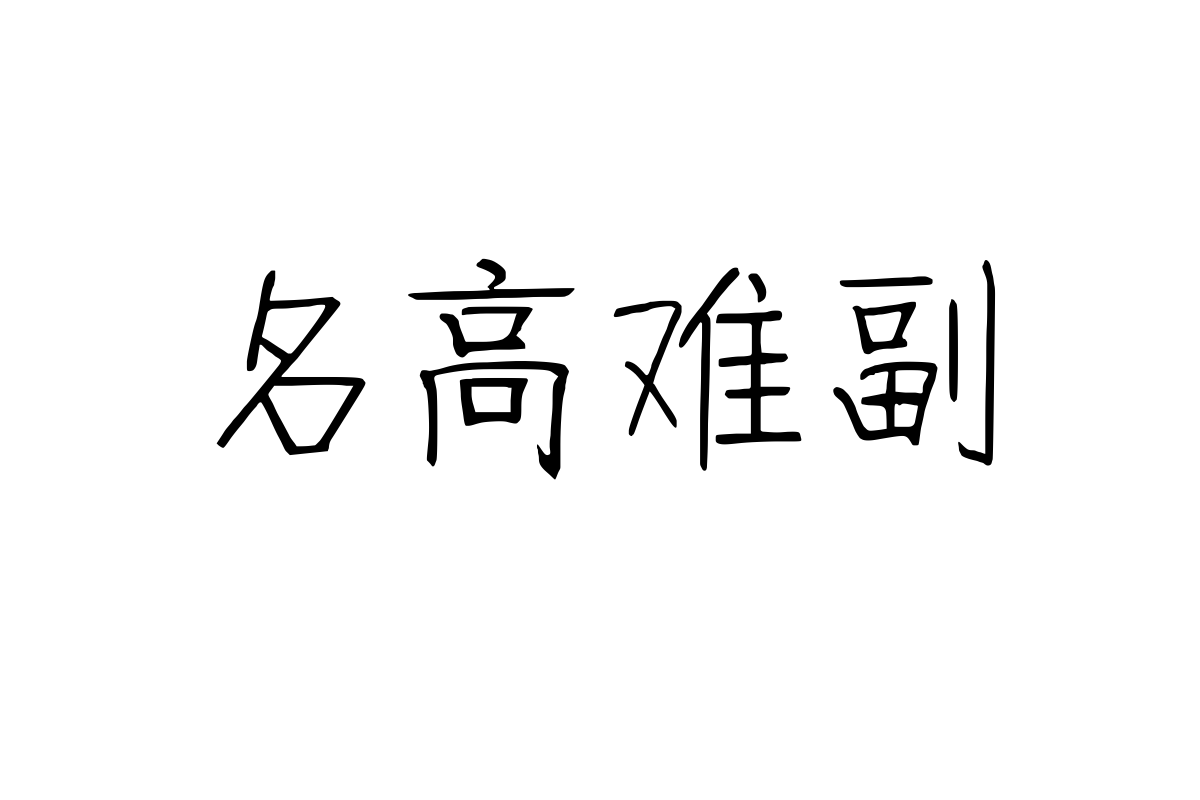
汉标孙运和酷楷字体是一套由汉标公司开发的中文手写体,旨在为用户提供一种独特的、个性化的手写体验。这套字体结合了传统书法的韵味与现代设计元素,具有很高的艺术价值和实用性。
1. 风格特点:汉标孙运和酷楷字体采用了传统的书写风格,笔画流畅自然,结构紧凑,具有较强的视觉冲击力。同时,该字体在保持原有风格的基础上,进行了一定程度的简化和优化,使得书写更加便捷。
2. 应用领域:汉标孙运和酷楷字体适用于各种需要手写输入的场景,如电子文档、名片、广告、海报等。此外,还可用于网页设计、软件界面、游戏角色设计等场景,为设计师提供更多的创作灵感。
总之,汉标孙运和酷楷字体是一款具有独特魅力的中文手写体,无论是从艺术价值还是实用角度来看,都具有较高的吸引力。